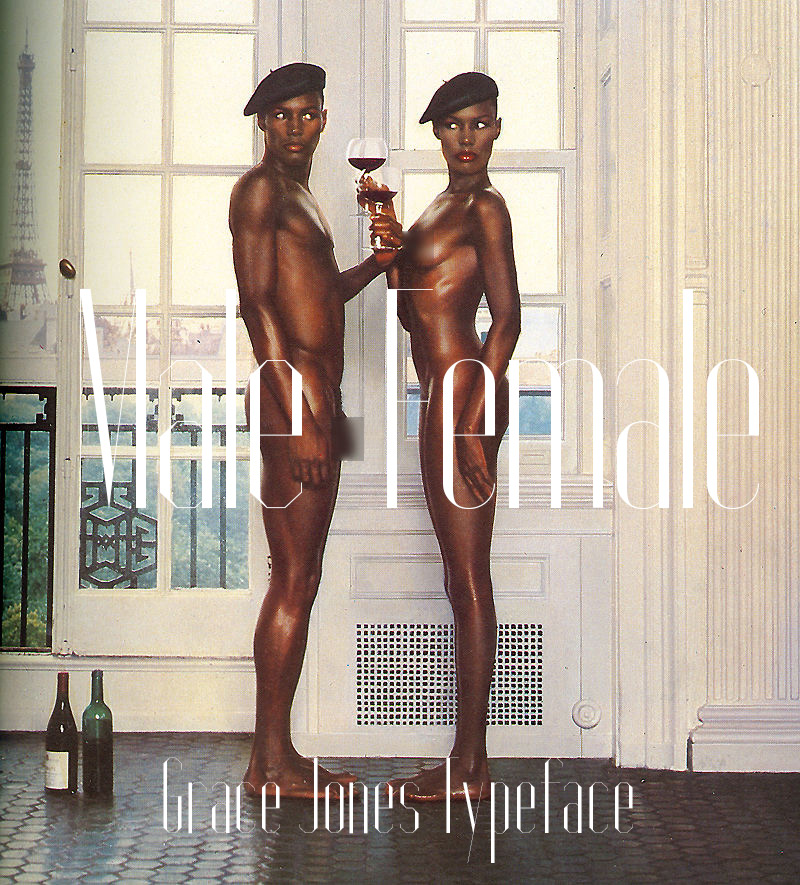
diesmal in ich auf der suche nach klassizistsichen antiquas die in naher vergangenheit bzw gegenwart durch innovative schriftgestalter eine neuauslegung erfahren haben. gibt eine geometrische bodoni? anlehnungen an klassiker wie beispielsweise walbaum oder didot mit hang zur exzentrik oder zum experiment?  die carmen ist hierbei bestimmt eine recht moderate vertreterin.
vertiefend würde ich gerne wissen, worauf die forumsleser gestoßen sind, welche ihnen bemerkenswert erscheinen und welche schriftgestalter oder foundries damit zusammenhängen.
Das a der Kepler Ext … zumindest dieser Buchstabe ist für mich eine Interpretation.
Ich muss da ja als erstes an Narziss denken:
ohja, grace jones ist schon aussergewöhnlich. diese richtung meinte ich.